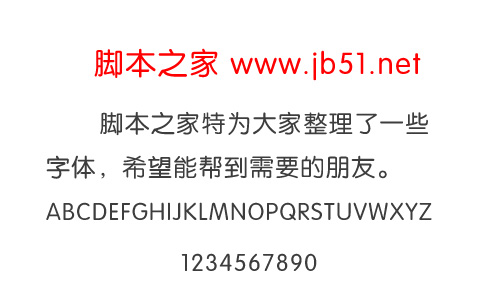
方正準(zhǔn)圓簡(jiǎn)體字體是方正字體庫(kù)中的一種字體,方正圓體家族的中宮寬松,字面大,起筆處與收筆處為圓形,折筆處呈圓弧狀。方正圓體家族的字形風(fēng)格舒展柔和,適用于女性、兒童和生活用品類的宣傳冊(cè)和包裝設(shè)計(jì)等。方正圓體家族包括3款字重,其中方正粗圓筆畫(huà)厚重飽滿,適用于標(biāo)題;方正準(zhǔn)圓筆畫(huà)粗細(xì)適中,適用于正文排版;方正細(xì)圓筆畫(huà)纖柔,也適用于正文排版。喜歡的朋友們可以前來(lái)下載使用。